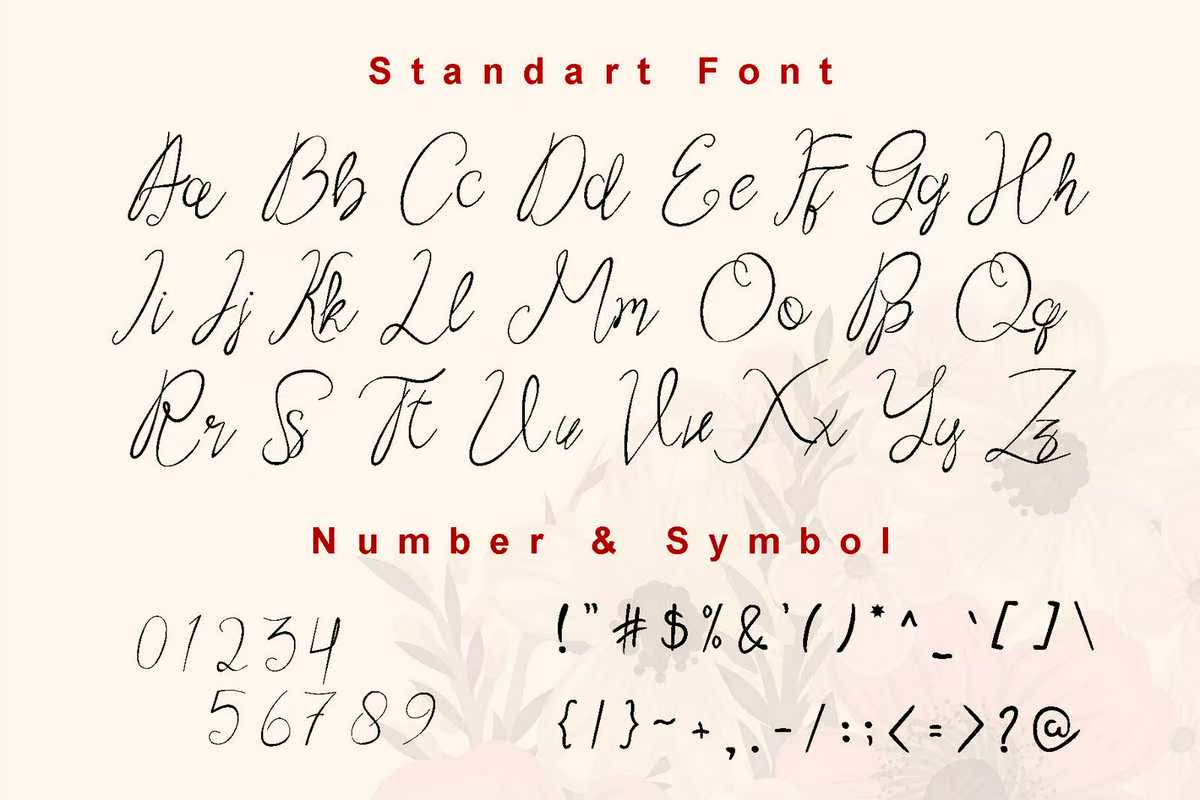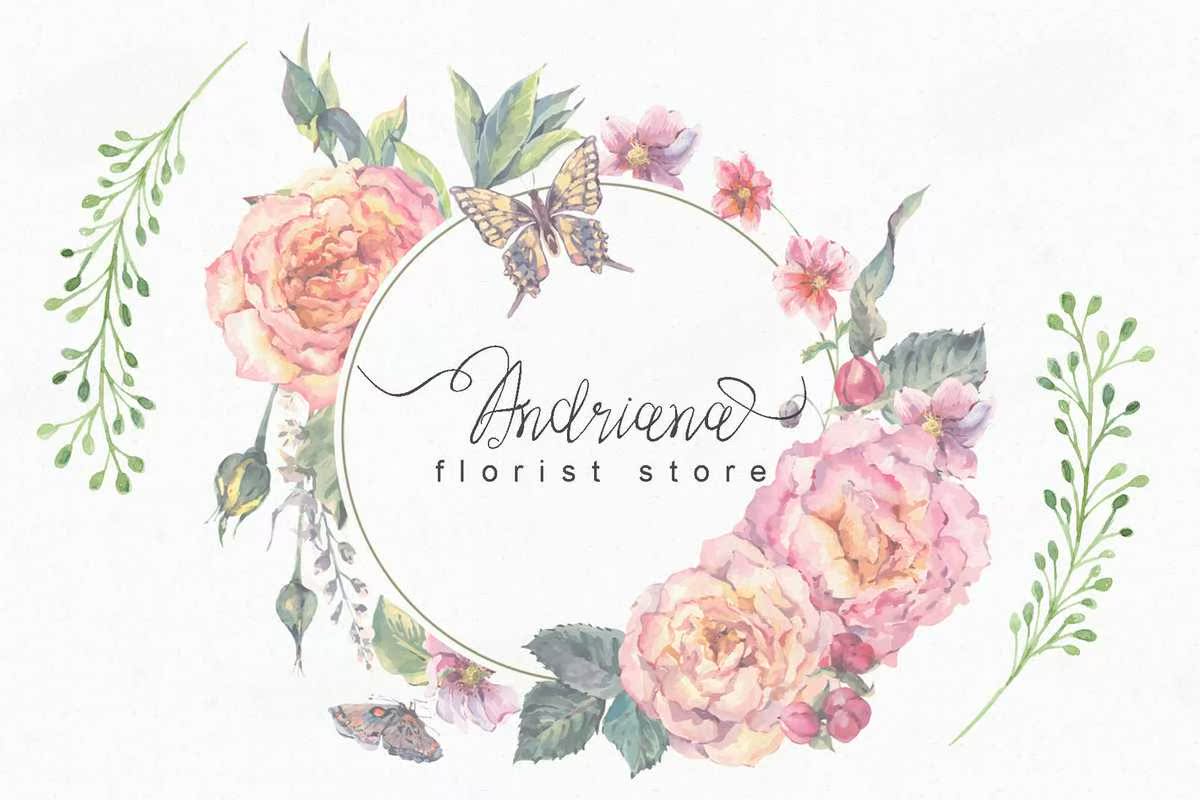
StayatHome将Legance简化为一个真正的外部字体和书写字体。无论您是否正在为项目重新查找FontsforInstagram或Caligraphyscript,此字体都将使任何创造性思维变成一件艺术作品!StayatHome将Legance简化为一个真正的外部字体和书写字体。无论您是否正在为项目重新查找FontsforInstagram或Caligraphyscript,此字体都将使任何创造性思维变成一件艺术作品!